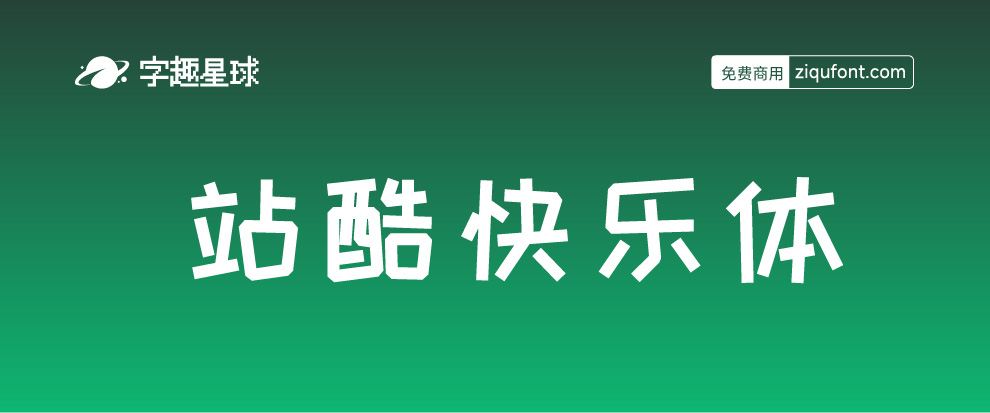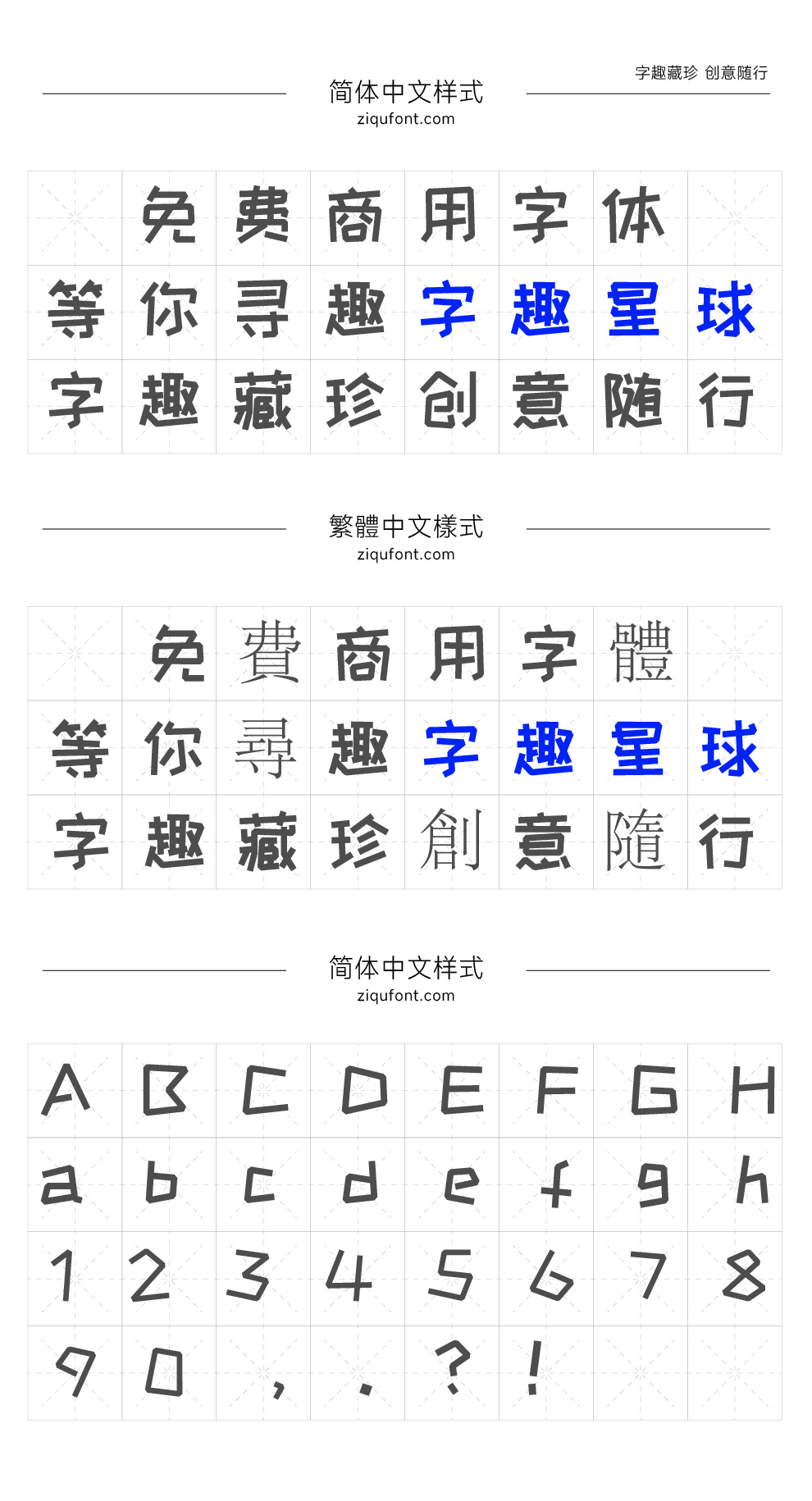
站酷快乐体
站酷快乐体由字体设计师刘兵克及100多位字体设计爱好者们共同完成。这套风格轻松活泼的字体也是继站酷高端黑之后,第二套由酷友集体创作完成,供所有人永久免费使用(可商用)的公益字体。
很显然,站酷快乐体,是一枚可爱有趣、活泼俏皮的个性字体。根据字体的形式特点,站酷快乐体可以很方便的应用在网页标题、促销主题、产品包装(如零售包装)等环境中,当然,你也可以用在漫画作品、电视节目这些环境里,只要你想用,就可以尽管用,因为站酷快乐体是免费的,是公益的,地球公民都可以任意使用!
• 4字字形错误:廊郡盟儒
• 4字轮廓有问题:腐蚯螓貘
• 69字字形错位:馇恽饪忾狲馔馀恻馄饨恺怃饩狍怄馑狯饷馓恸饽猬廪恹犷饧忏馍惬饬犸馐怆猡饴怿猕赓馊悭饫怅猃馕庑钛钌睐钚钊眦钕钋眍钗钇钫钔钆钤钐羁钣钏罴钜钍睑
• 改动7个标点符号的字形、位置:、。,:;!?
关于站酷快乐体
【站酷快乐体】是由字体设计师刘兵克组织其字体设计学员进行的字体设计活动,由刘兵克提供字形框架和设计规范,由100多位学员朋友按照各自字体内容设计出基本字形,再由刘兵克字体设计工作室成员杨康和吴少杰进行设计修改和调整完成。发布于2015年9月。
【站酷快乐体2016修订版】,是在“站酷快乐体”基础上进行的大幅修改与提升, 本次修订工作的设计前期,由刘兵克学员团队和工作室团队共同完成,设计后期,由刘兵克进行了逐一修改与调整,经过多轮校审之后,于2016年6月正式对外公布和提供下载,整个工作耗时7个月。
字体应用示例
站酷快乐体